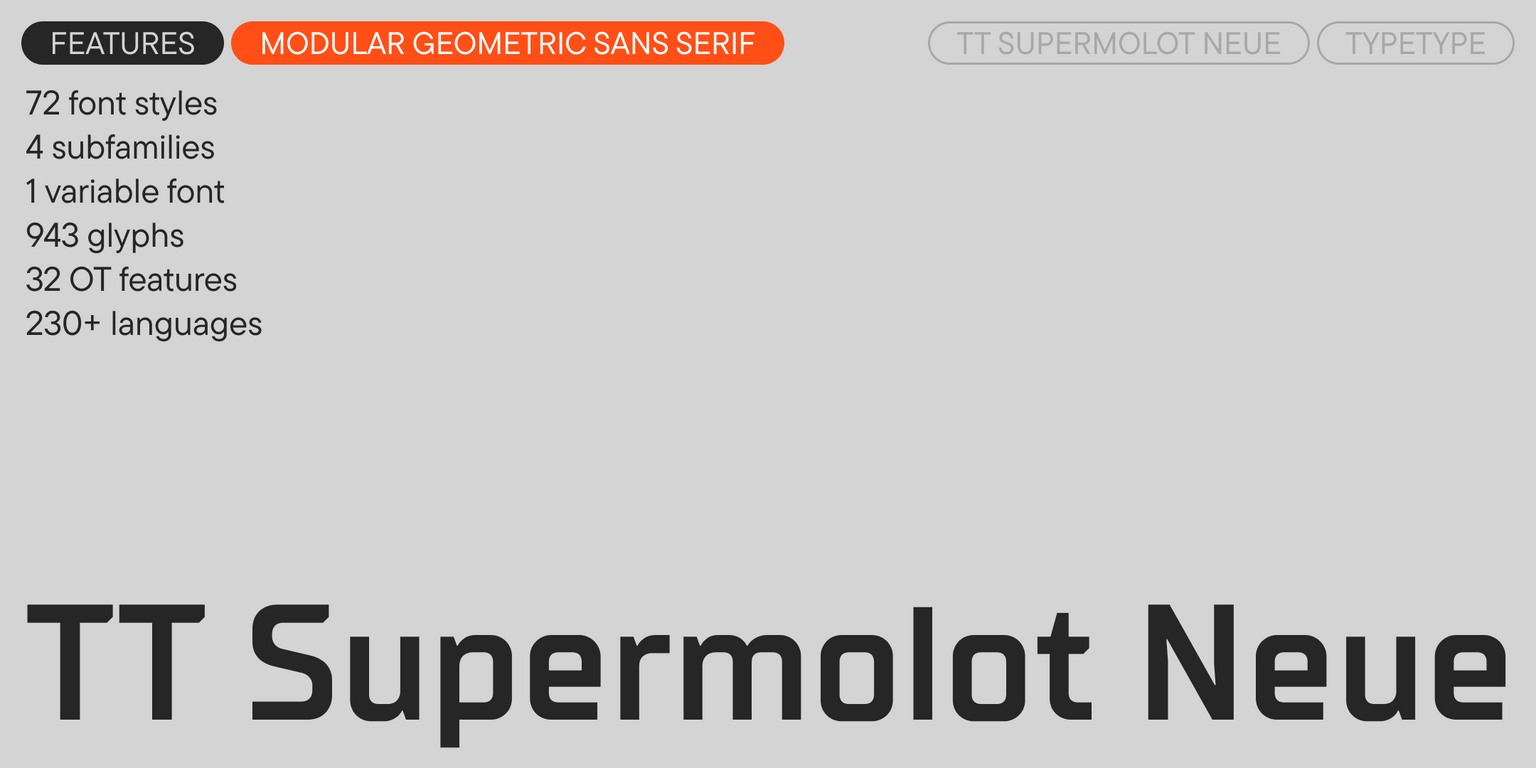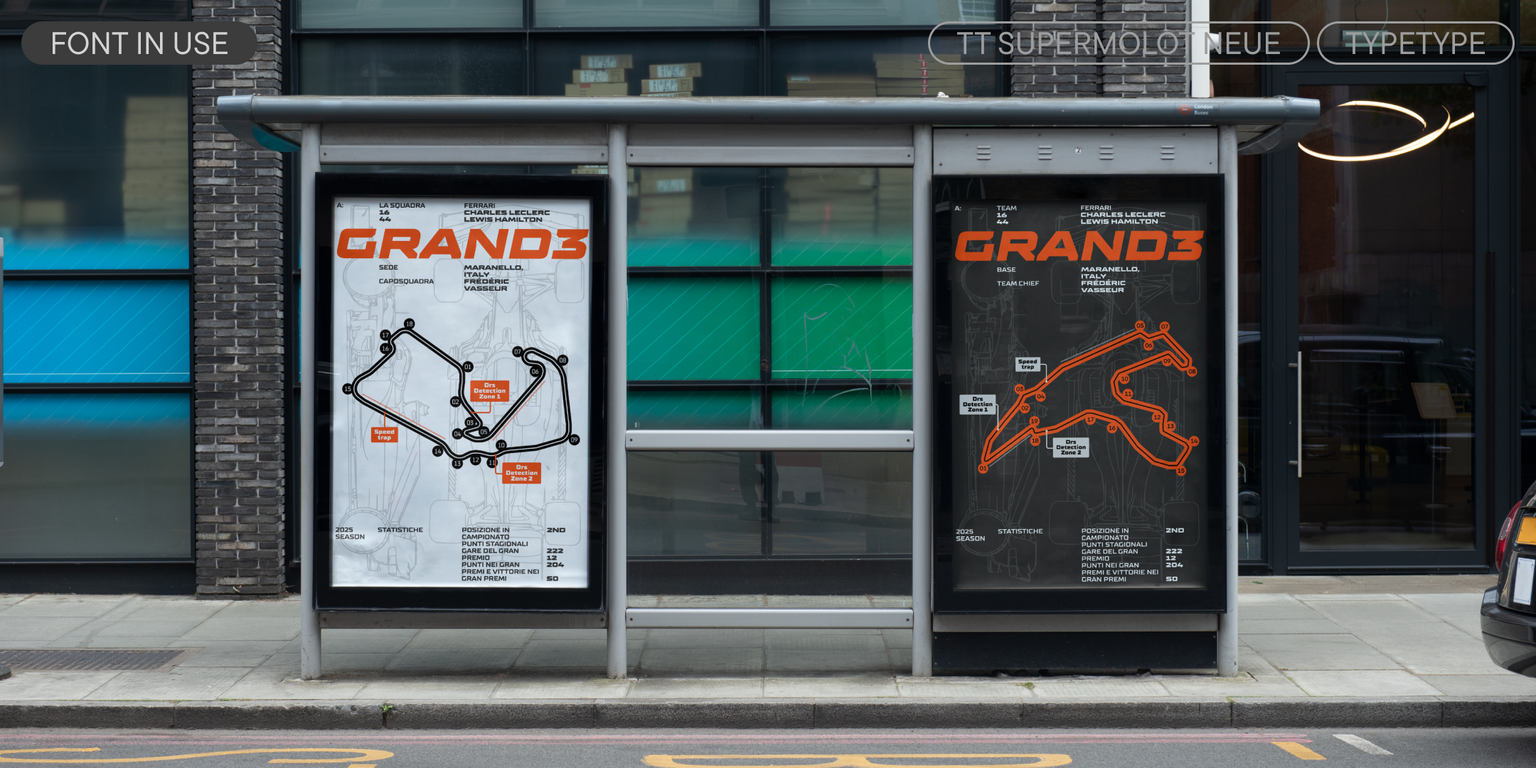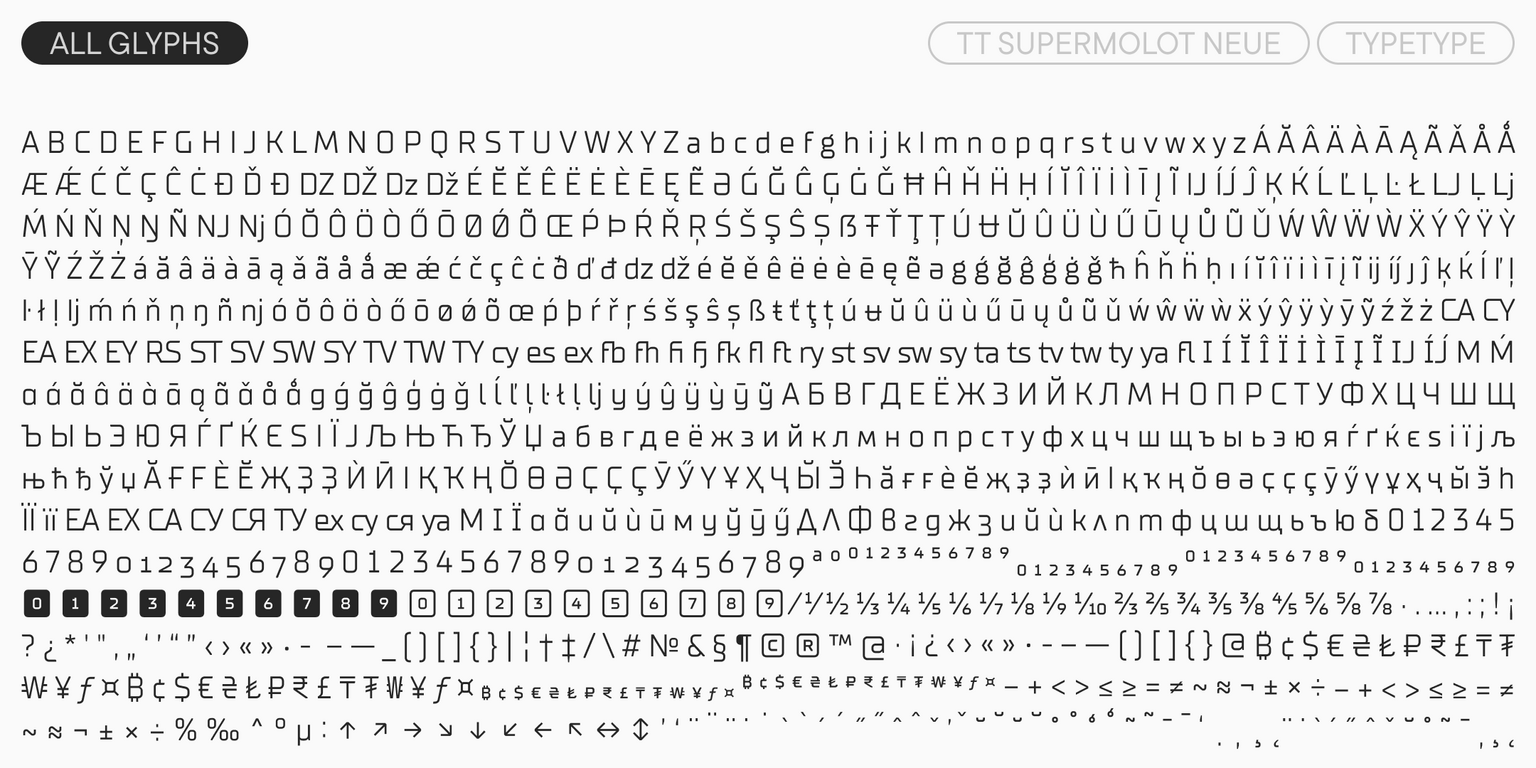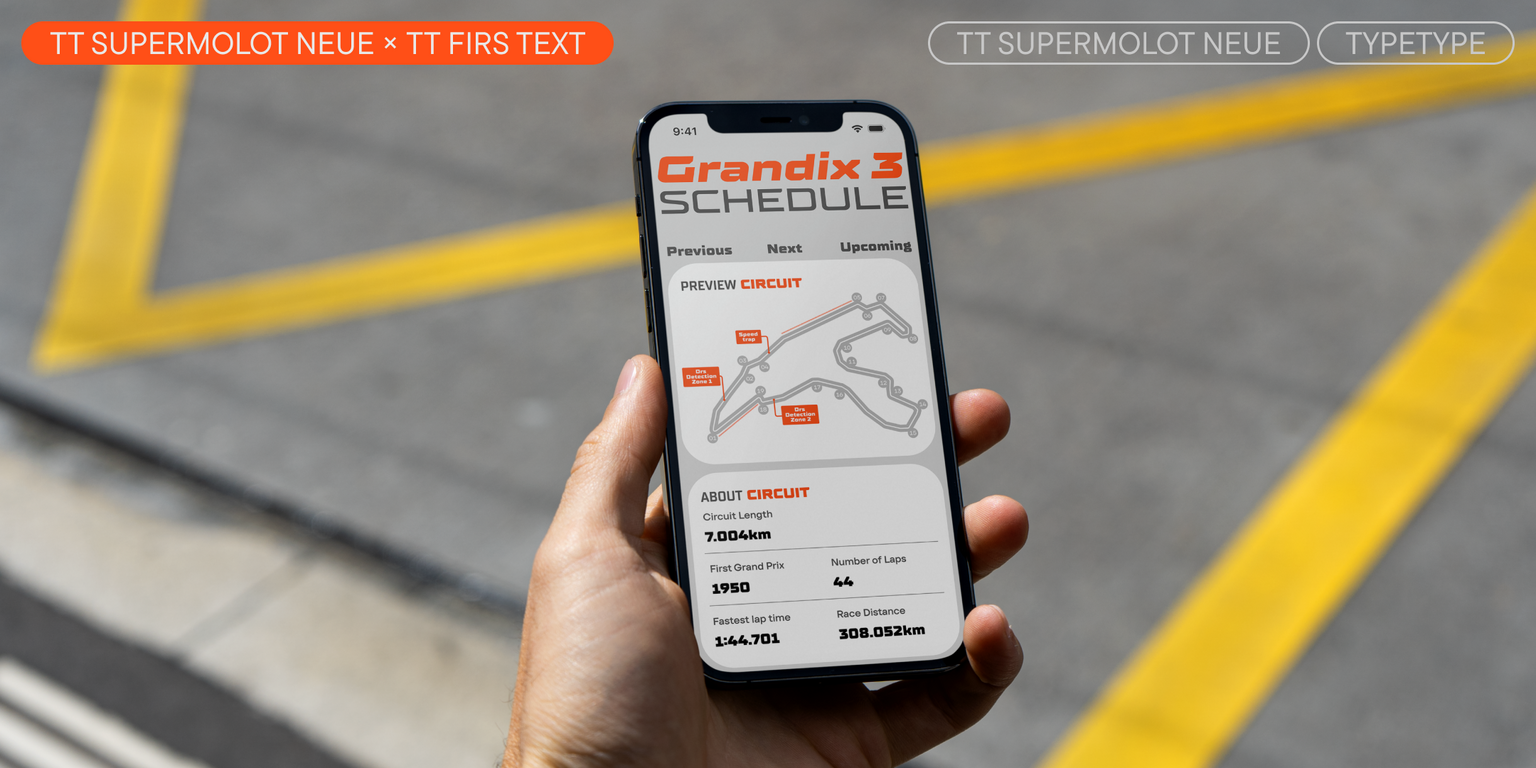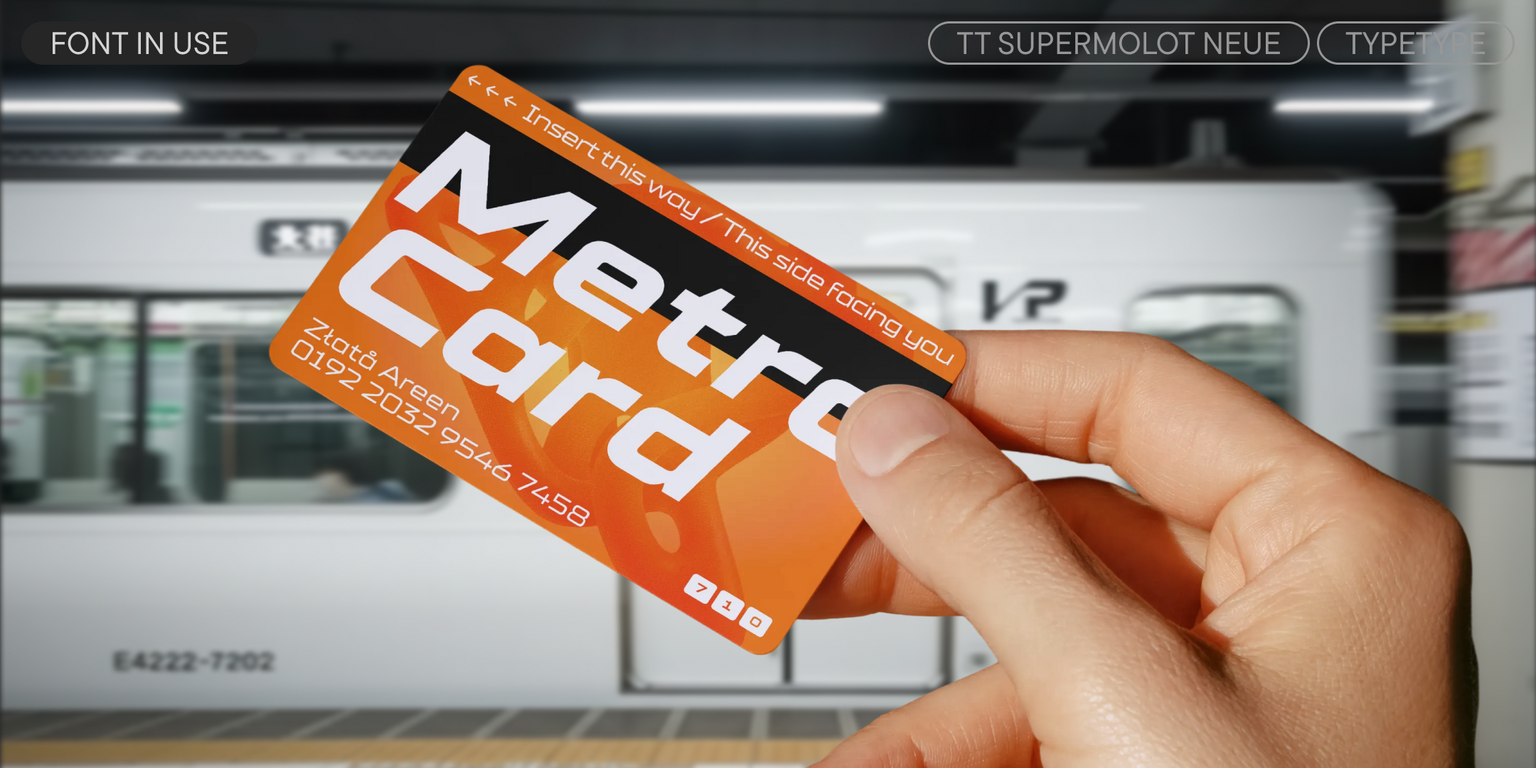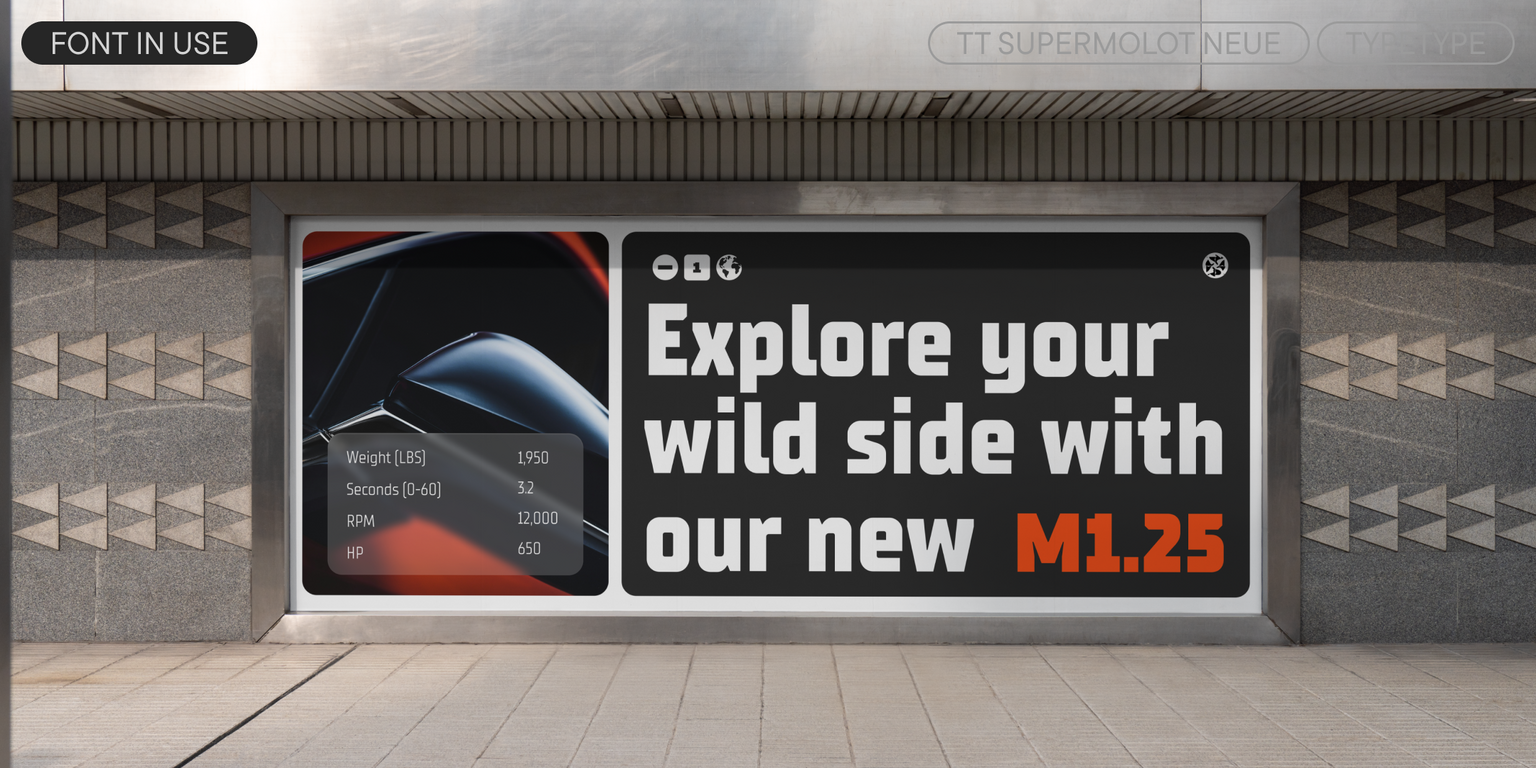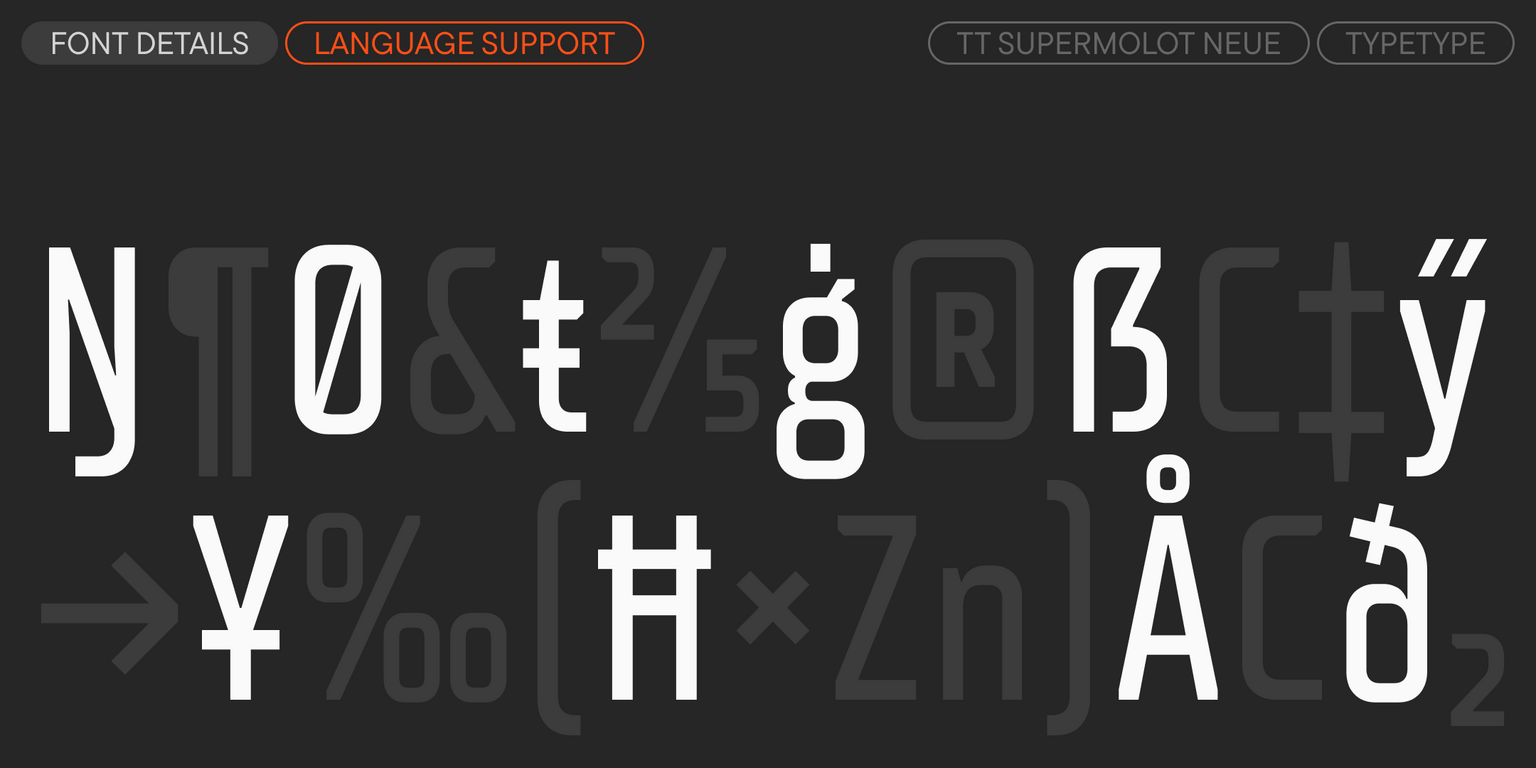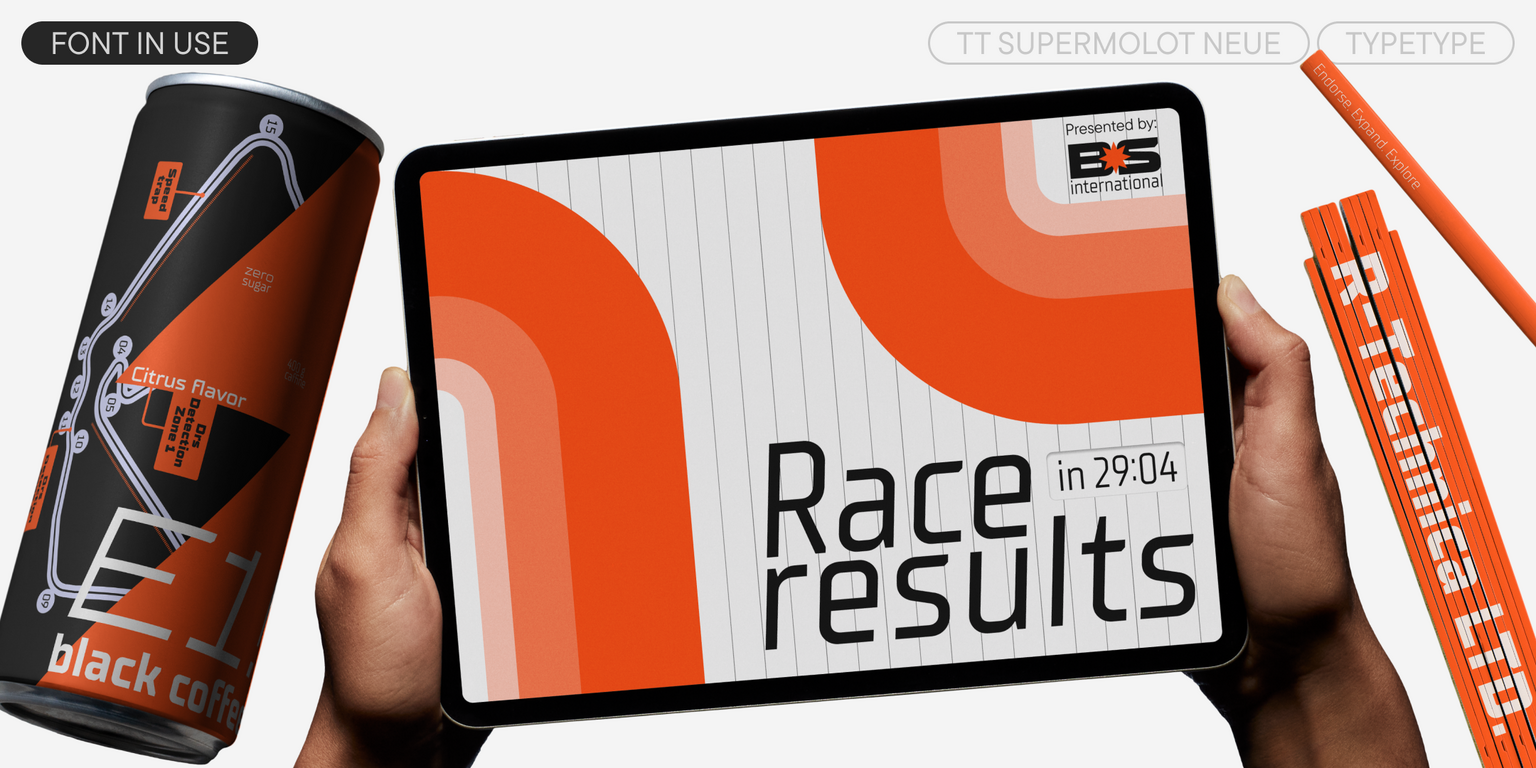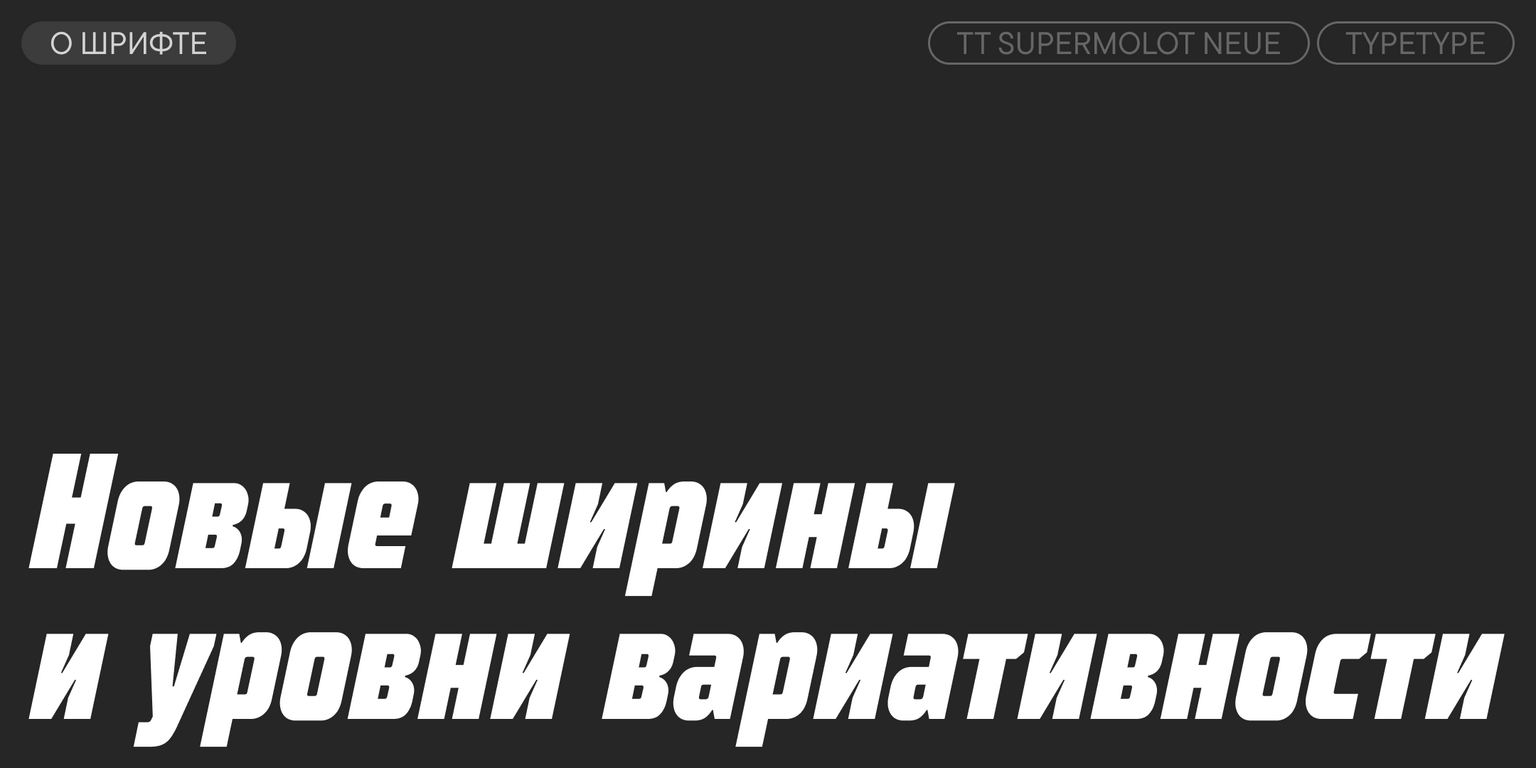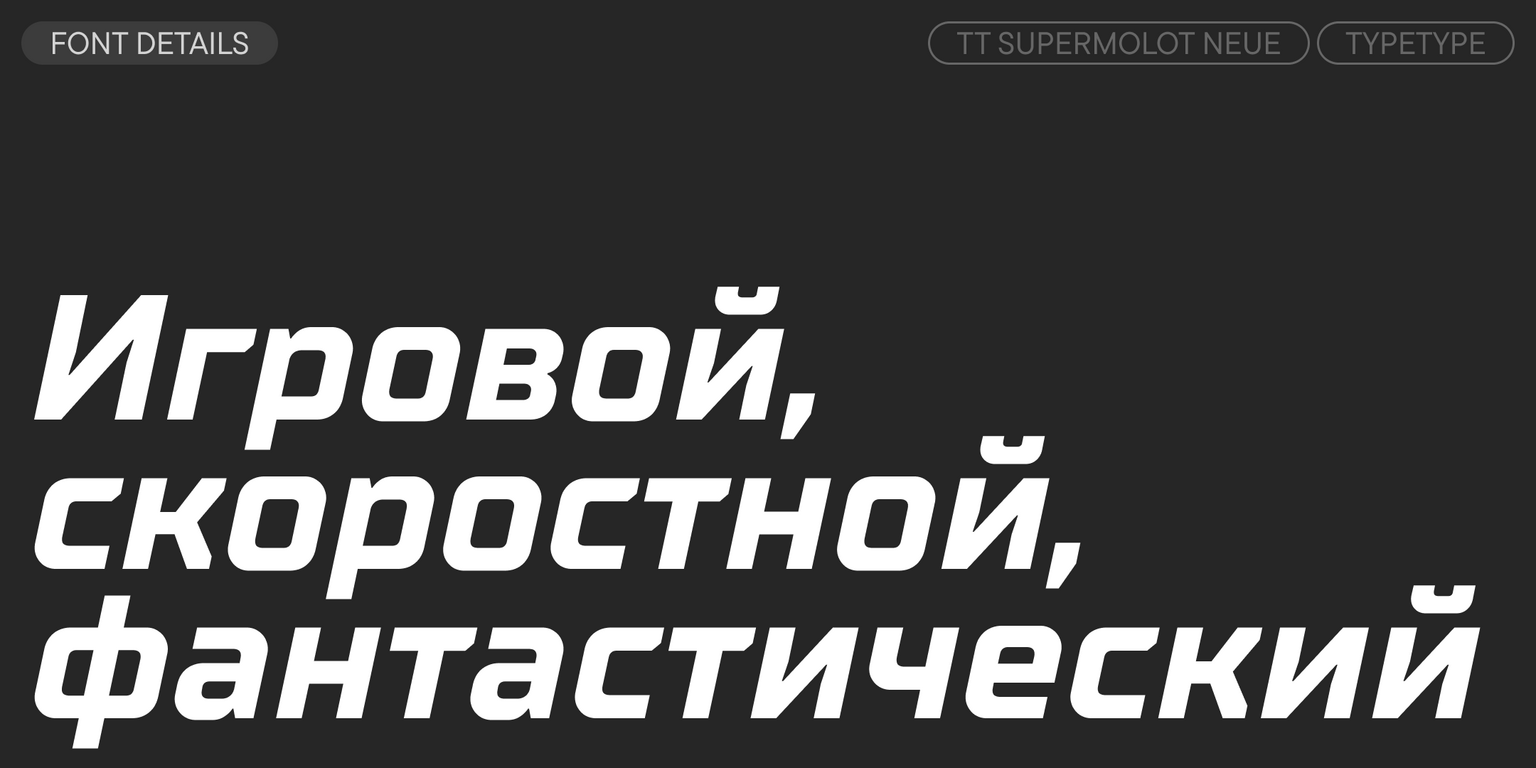
TT Supermolot Neue
TT Supermolot Neue — ТТ Супермолот Нью
Произносится «ТТ Супермолот Нью». «Supermolot» — производное слово от super (с английского «супер») и molot (транслитерация слова «молот»). «Neue» — в переводе c немецкого «новый». Буквы «TT» являются аббревиатурой названия компании.
TT Supermolot Neue — технологичный модульный гротеск с футуристическим настроением и мощным функционалом. Яркость его характера сочетается с универсальностью применения.
TT Supermolot Neue
TT Supermolot Neue — технологический модульный гротеск, созданный для интерфейсов игр
TT Supermolot Neue
Путь нашей компании начался с первой версии TT Supermolot: мы создали его в далеком 2013 году на базе классического бесплатного шрифта Molot. За прошедшие 10 лет эта гарнитура многократно обновлялась, переосмысливалась и расширялась. Шрифт обрел особую популярность в игровой индустрии: разработчики активно используют его в интерфейсах современных игр. В 2024 году мы снова обновили TT Supermolot. Добавили большое количество языков, основанных на кириллице, и расширили латинские языки. Кроме того, дополнили шрифтовое семейство внушительным списком служебных знаков, и теперь его функционал стал гораздо мощнее.